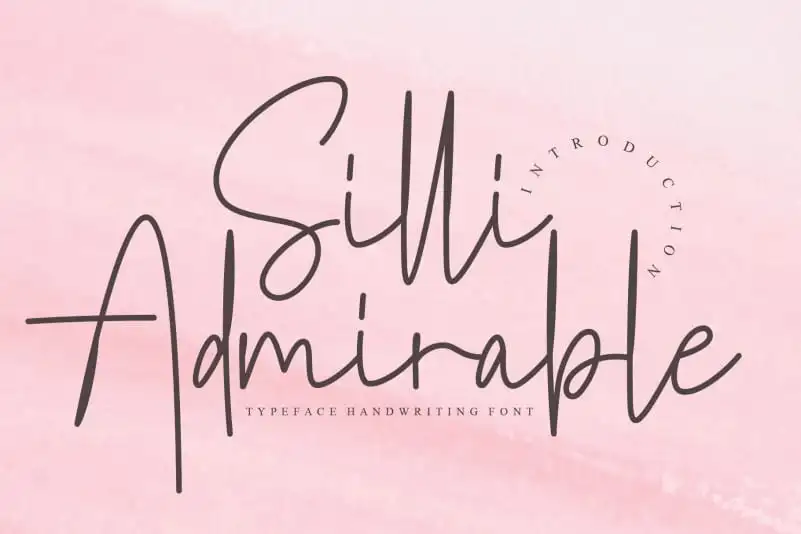
Silli Admirable Handwritten Font – Download Grátis
A Silli Admirable Handwritten Font é uma delicada escolha para quem valoriza a autenticidade na tipografia. Seu traço fluido e elegante traz a personalidade única de um autêntico escritor, criando um visual rico e sofisticado em qualquer projeto. Com uma abordagem totalmente hand-made, essa fonte captura detalhes sutis que se transformam em elementos distintivos. Como a criação é feita diretamente por um artista, não há duas formas iguais — cada palavra escrita com a Silli Admirable Handwritten Font é única e carrega o rastro da mão do designer. Este produto da creativeletter oferece uma experiência excepcionalmente especial aos seus clientes. Com Silli Admirable, você pode trazer um toque autêntico e único à sua obra, seja em um site personalizado ou uma capa de livro impresso.